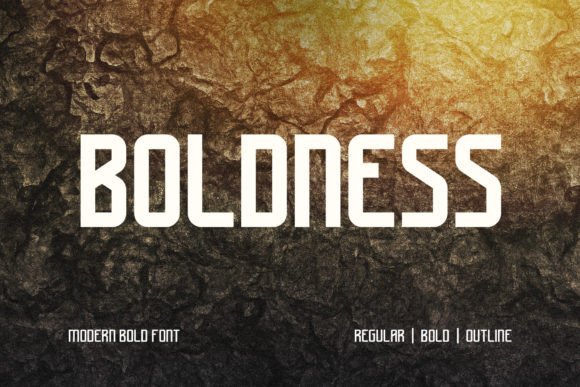
Fuente de exhibición audaz y fuerte para carteles y productos
Boldness es una impactante familia tipográfica sans-serif que combina una geometría limpia con opciones de grosor en negrita. Su diseño incluye variantes Regular, Bold y Outline, lo que le ofrece flexibilidad para todo, desde texto sutil hasta titulares y logotipos impactantes. Gracias a su diseño legible y con presencia, Boldness funciona igualmente bien en proyectos de diseño impresos y digitales, incluyendo productos, empaques, carteles y gráficos web.
- Múltiples estilos (normal, negrita, contorno): brinda flexibilidad tipográfica para titulares, cuerpo de texto y uso decorativo.
- Aspecto sans-serif limpio y moderno: funciona con muchos temas de diseño y paletas de colores sin opacar otros elementos
- Altamente legible, incluso en tamaños grandes, lo que lo hace ideal para carteles, señalización, empaques y diseños de productos.